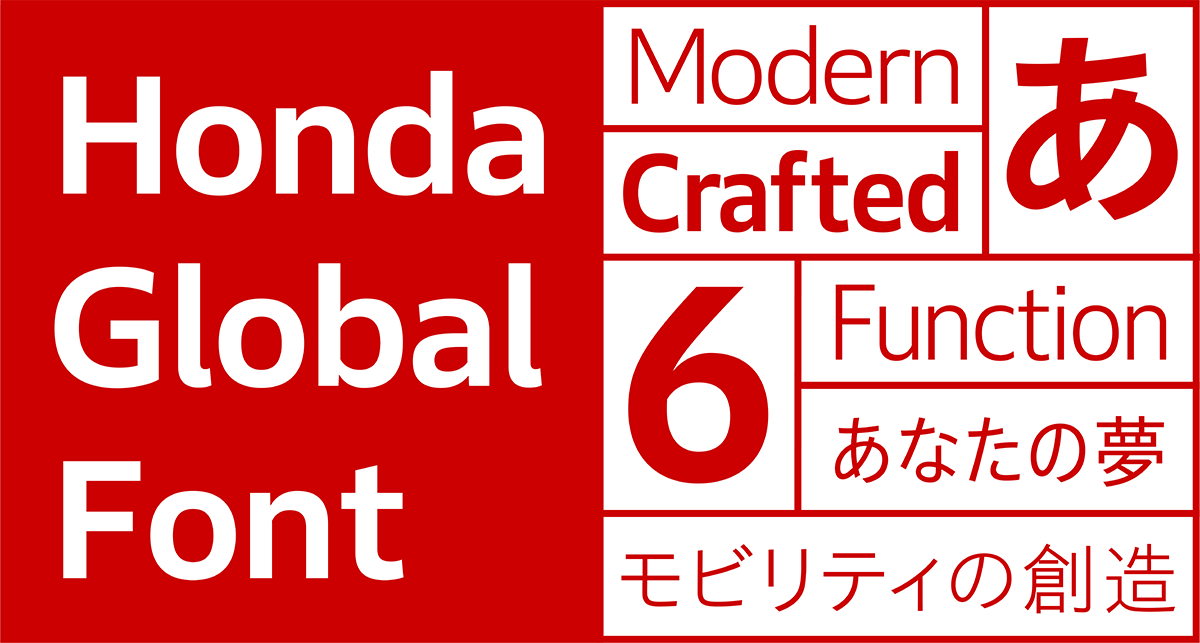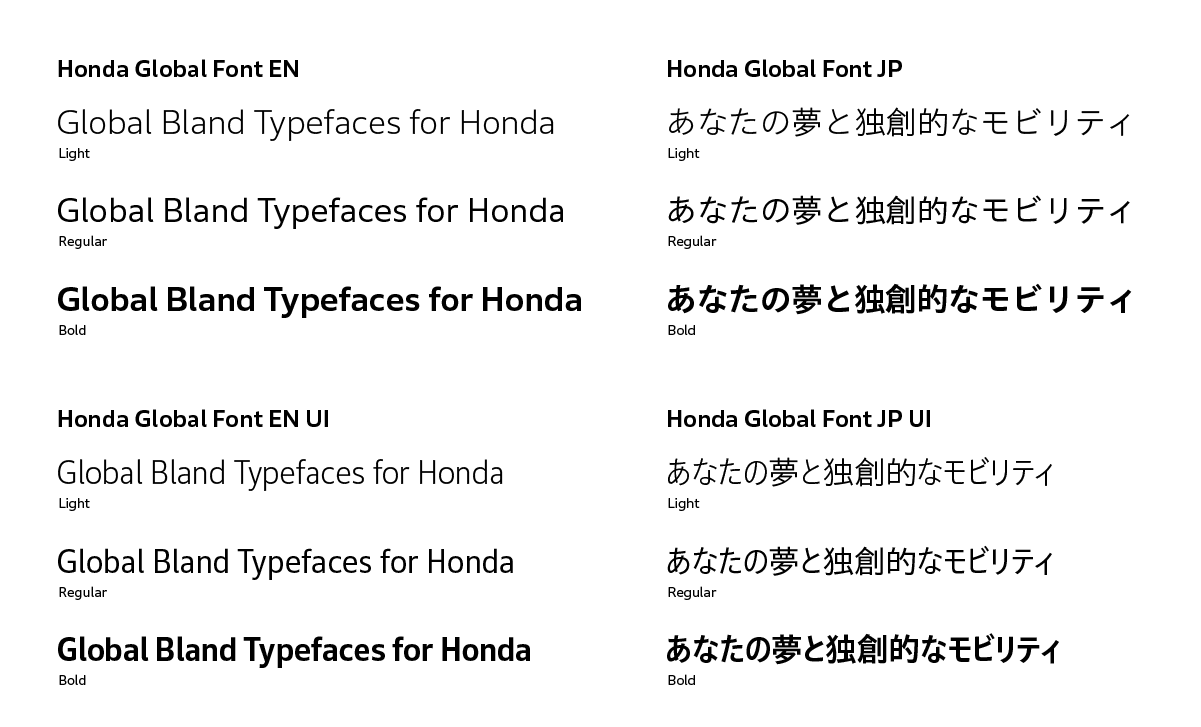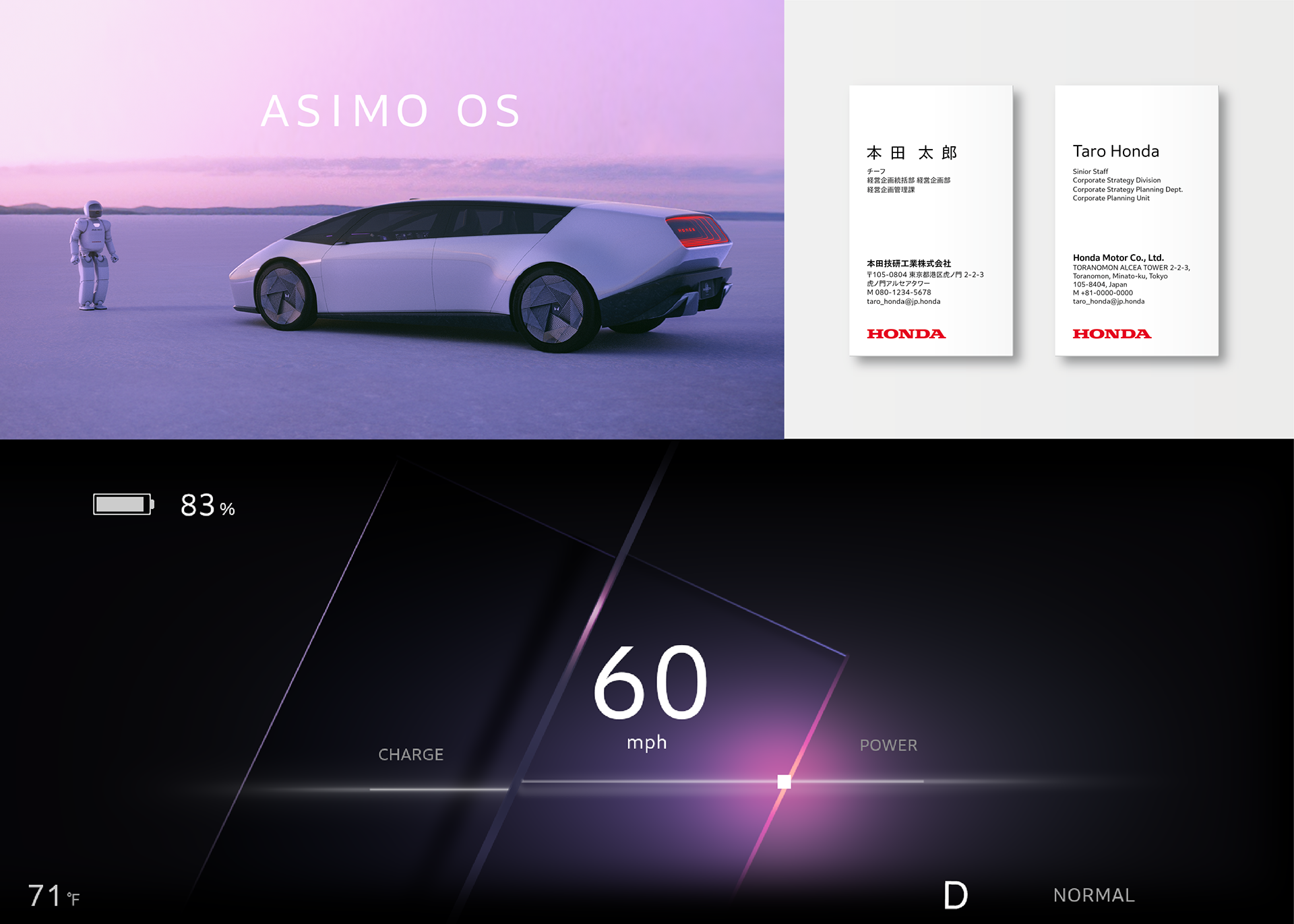
주식회사 모리사와(株式会社 モリサワ, 이하 모리사와)가 혼다기연공업 주식회사(本田技研工業株式会社, 이하 Honda)의 기업전용 폰트 「Honda Global Font」패밀리를 개발했습니다.
Honda는 다양한 모빌리티 및 서비스를 전 세계 고객에게 제공하고 있는 종합 모빌리티 컴퍼니입니다. 100년에 한 번 있을 커다란 변혁기를 맞이하면서, 2001년에 제정한 글로벌 브랜드 슬로건인 「The Power of Dreams」를 2023년에 재정의하고, 이를 「Honda 브랜드 매니지먼트의 출발점」으로 자리매김 하였습니다. 꿈이 담긴 상품・서비스를 비롯한 모든 기업활동을 통해, 이 재정의에 담긴 뜻을 구현하면서, Honda다움을 더욱 부각시키고, 계속해서 존재가 기대되는 기업이 되어가는 것을 목표로 하고 있습니다.
이번에 개발된 「Honda Global Font」패밀리는 라틴 폰트인 「Honda Global Font EN」과 일본어 폰트인 「Honda Global Font JP」, 그리고 장체 너비로 제작된 UI폰트입니다. Honda의 브랜드 디자인을 다루는 브랜드・커뮤니케이션 센터 팀과 모리사와 프로젝트 멤버가 양사의 경계를 넘나들며 아이디어를 주고 받으며 개발이 진행되었습니다.
라틴 폰트인 Honda Global Font EN은 모리사와의 「Clarimo UD PE」를 기반으로 커스터마이즈한 산세리프체입니다. 큰 자면과 열린 개구부 처리는, 주행 중에도 글자를 순간적으로 인지하기 쉽도록 고려하여 만들어졌습니다. 또한 안정감 있는 의연한 골격과 힘찬 획의 흐름, 획의 끝까지 의식을 담은 정중한 표현은 선진적이면서도 장인정신이 느껴져, 모던하면서도 수작업으로 만든 듯한 인상을 자아내고 있습니다.
그리고 일본어 폰트인 Honda Global Font JP는 모리사와의 「아오토고딕」을 기반으로 하면서, 유한회사 지유코보의 서체설계사인 도리노우미 오사무(鳥海修)가 감수를 맡아 개발한 고딕체입니다. 라틴과 동일하게 시인성 등의 기능면을 고려하면서도, 가나의 가로획이 오른쪽으로 상승하는 경사를 주어, 일본어 특유의 자연스러운 리듬감을 표현하고 있습니다. 획의 억양과 골격에는 붓의 뉘앙스를 넣어, 한 글자마다 풍부한 표정과 단단한 인상을 주는 폰트입니다.